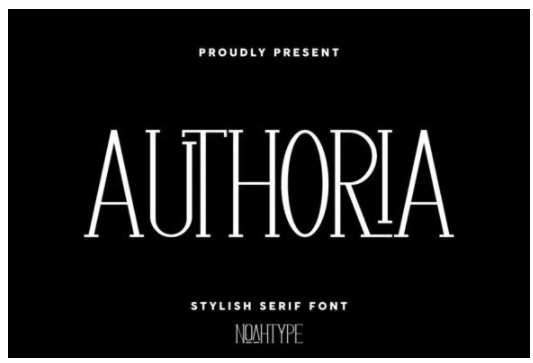
Creativefabrica Authoria Font 2021
[Creativefabrica] Authoria Font (2021)
Authoria - это минимальный и высокий шрифт с засечками.
Его можно легко подобрать к невероятно большому количеству проектов, поэтому добавьте его к своим творческим идеям и обратите внимание на то, как он их выделяет!